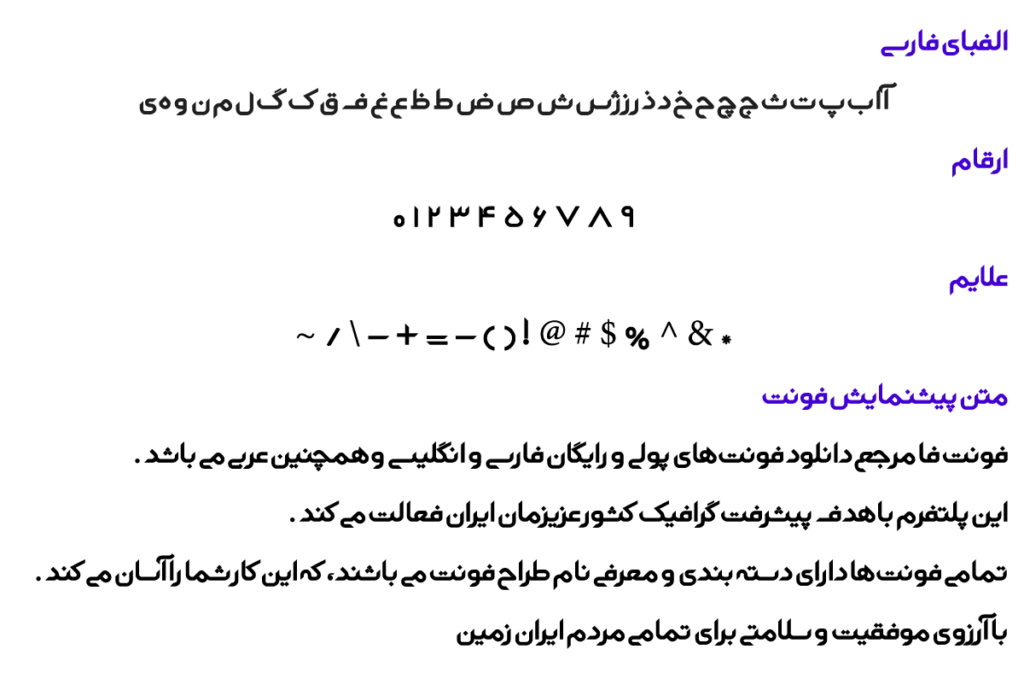
فونت فارسی آسمان – G Aseman
سال ساخت فونت: 1395
طراح فونت: قاسم نجاری نوع فونت: فونت تایپوگرافی
توضیحات و معرفی فونت آسمان
فونت فارسی آسمان ( G Aseman ) از مجموعه فونت های آزاد می باشد، همینطور نوع فونت تایپوگرافی می باشد.
فونت زیبای مرتبط توسط قاسم نجاری در سال 1395 طراحی و ساخته شده است.
تمامی حروف این فونت بر اساس تایپ فیس بانک سامان طراحی شده و با تغییرات گستردهای اجرا شده است.
تلاش شده تا این فونت نسبت به نمونه های موجود، هویتی متمایز داشته باشد و امید است که این هدف محقق شده باشد.
همینطور فونت آسمان در یک وزن معمولی است.